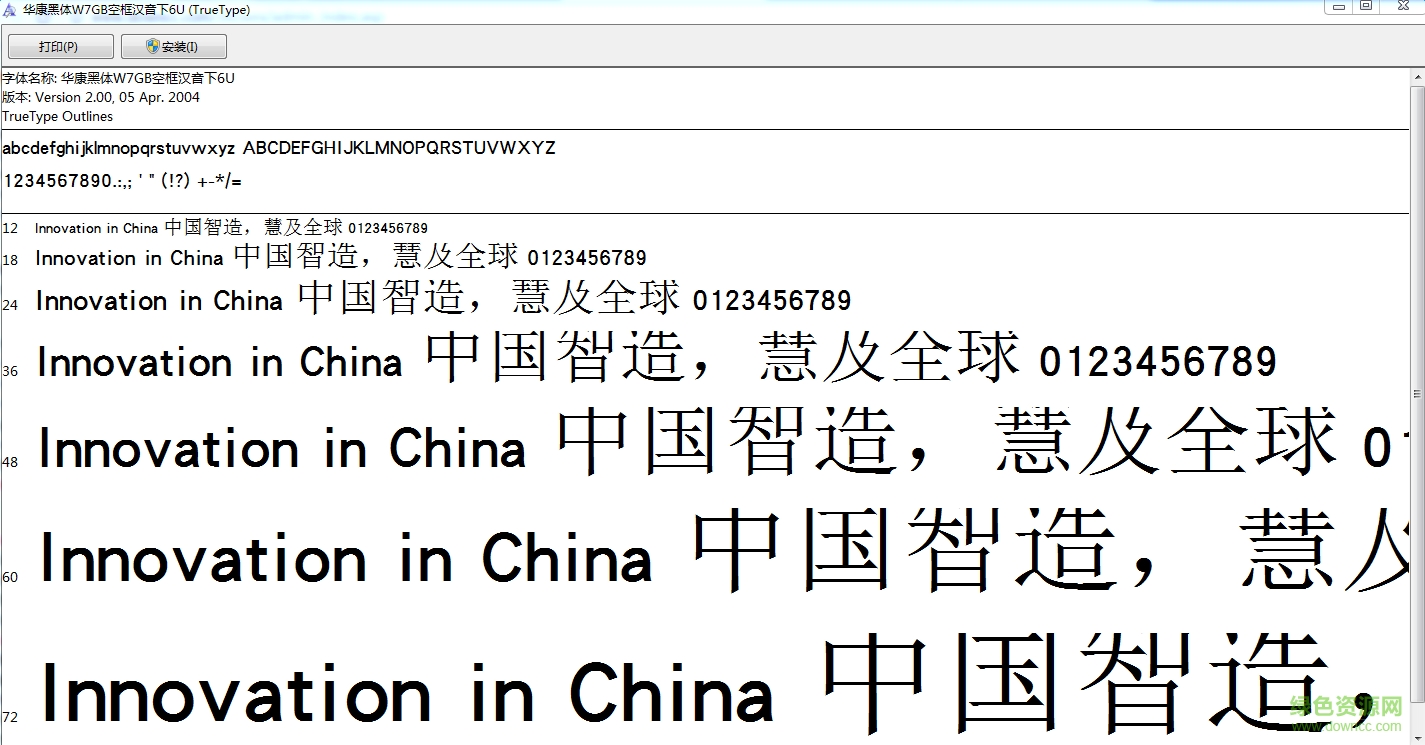
華康黑體W7GB空框漢音下U字體是一款華康類w7gb黑體字體軟件,黑色的字體給人非常正規(guī)的感覺,深受廣大年輕人的喜愛,還有更多好看字體盡情期待,歡迎到綠色資源網(wǎng)下載體驗(yàn)!
華康黑體W7GB空框漢音下U是一款華康類w7gb的黑體字,字體效果比較黑,喜歡黑體字的朋友可以下載使用看看效果如何。